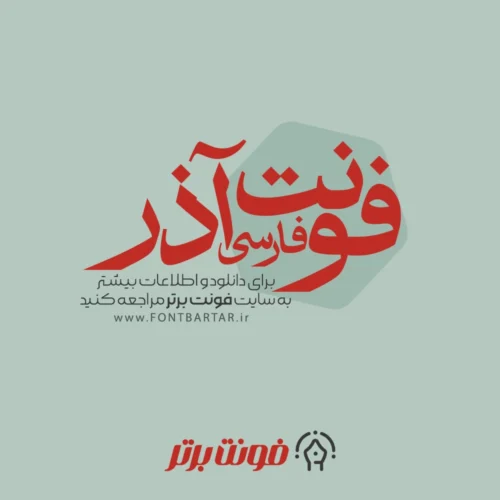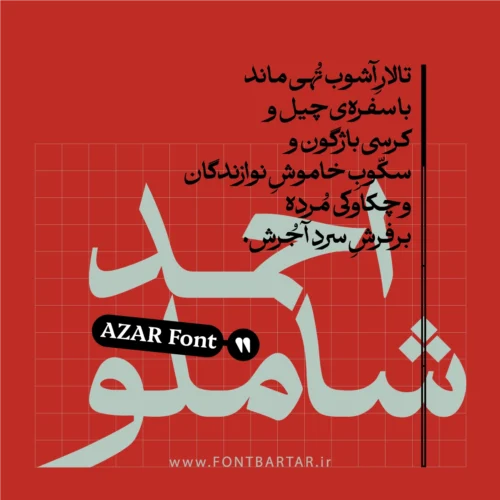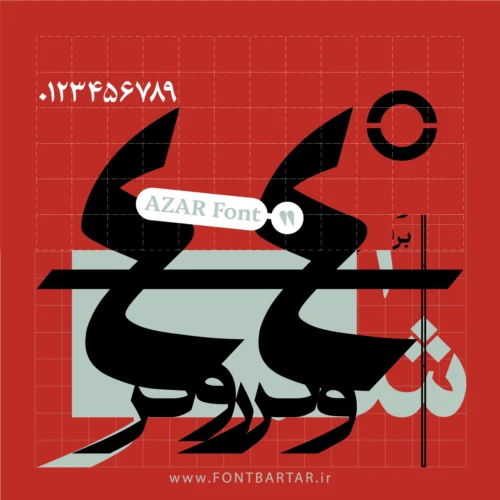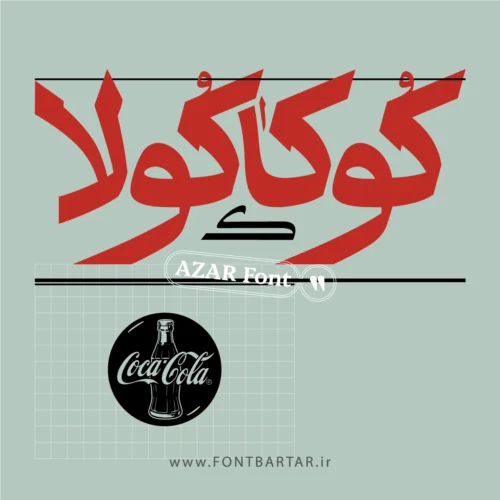
دانلود فونت آذر
فونت فارسی آذر
دانلود فونت آذر با الهام از حرکات ثلث طراحی شده اما دارای چهره و تناسباتی متفاوت است تا بتواند تبدیل به یک فونت نرم افزاری شود. دانلود فونت فارسی آذر با ظاهری مناسبِ عناوین و تیتر کتاب‌ها و روزنامه‌ها، از سویی پاسدار ریشه‌های کهن کلاسیک است و از سوی دیگر ظاهری پیراسته و امروزی دارد.
زیبایی‌شناسی و ویژگی‌های منحصربه‌فرد حروف در دانلود فونت فارسی برای اینشات به شکلی طراحی شده‌اند که با ساختارهای نوین طراحی و استانداردهای ساخت دانلود فونت فارسی با فرمت ttf همخوان باشد. تناسبات و قواعد کلیهٔ کاراکترها بازنگری و اصلاح شده‌اند. با حفظ روح اصلی، کاراکترهای جدید به مجموعه افزوده شده‌اند.